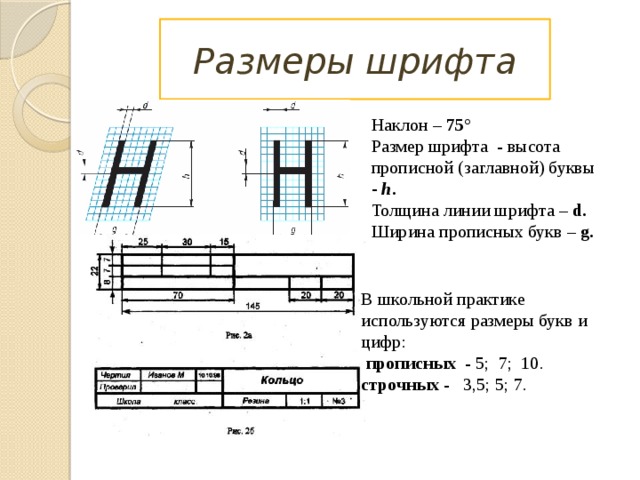
"Чертёжный шрифт"
Правила написания чертёжного шрифта. Высота и ширина букв и цифр.
Толщина линии обводки.
Расстояние между буквами, словами и основаниями строк.
«"Чертёжный шрифт"»
Чертежный шрифт
Чертежный шрифт ГОСТ 2.304-81 высота и ширина букв и цифр толщина линий обводки  расстояние между буквами, словами и основаниями строк
Чертежный шрифт ГОСТ 2.304-81
• высота и ширина букв и цифр
• толщина линий обводки
• расстояние между буквами, словами и основаниями строк
Размеры шрифта Наклон – 75° Размер шрифта - высота прописной (заглавной) буквы - h . Толщина линии шрифта – d. Ширина прописных букв – g.  В школьной практике используются размеры букв и цифр:  прописных - 5; 7; 10. строчных - 3,5; 5; 7.
Размеры шрифта
Наклон – 75°
Размер шрифта - высота прописной (заглавной) буквы - h .
Толщина линии шрифта – d.
Ширина прописных букв – g.
В школьной практике используются размеры букв и цифр:
прописных - 5; 7; 10.
строчных - 3,5; 5; 7.
Параметры № Ширина прописных (заглавных) 1 букв и цифр – g  Размер h Б, В, Д, И, Е, 4, 2 5 Ж, Ф, Ш, Щ 3 7 3 10 4 4  А, М, Ы, Х, Ю 4 6 6 4 5 Г, Е, З, С, 2,3,5,6,78,9 8 5 3  1 7 4 2 5 2 3 № Ширина строчных букв – g 1 Размер h 2 3 з, с а, б, в, г, д, е, и, к, л, н, о, п, р, у, х, ц, ч, ь, э, я 5 2 3 4 7 3 2,5  м, ы, ю, ъ 4 3,5 3 ж, т, ф, ш, щ 5 4 3,5 6 5 7 Параметры Размер шрифта Расстояние между буквами, цифрами и знаками - a 5 Расстояние между словами - e 7 1 Расстояние между основаниями строк - b 10 1,4 3 2 4,2 8,5 6 12 17
Параметры
Ширина прописных (заглавных)
1
букв и цифрg
Размер h
Б, В, Д, И, Е, 4,
2
5
Ж, Ф, Ш, Щ
3
7
3
10
4
А, М, Ы, Х, Ю
4
6
4
5
Г, Е, З, С, 2,3,5,6,78,9
8
5
3
1
7
4
2
5
2
3
Ширина строчных буквg
1
Размер h
2
3
з, с
а, б, в, г, д, е, и, к, л, н, о, п, р, у, х, ц, ч, ь, э, я
5
2
3
4
7
3
2,5
м, ы, ю, ъ
4
3,5
3
ж, т, ф, ш, щ
5
4
3,5
6
5
7
Параметры
Размер шрифта
Расстояние между буквами, цифрами и знаками - a
5
Расстояние между словами - e
7
1
Расстояние между основаниями строк - b
10
1,4
3
2
4,2
8,5
6
12
17
Правила написания чертежного шрифта:     1. Все надписи на чертеже должны быть выполнены от руки. 2. Начертание букв выполняйте по частям. Движение руки при выполнении прямолинейных элементов букв осуществляется сверху вниз или слева направо, а закругленных — движением вниз и влево или вниз и вправо. Стрелка указывает направление движения рук. 3. Одинаковые элементы различных букв, цифр, знаков следует выполнять одним и тем же приемом, что способствует выработке автоматизма при их написании. 4.Выдерживайте заданный наклон шрифта с помощью направляющих штрихов. 5. Строго соблюдайте конструкцию каждой буквы и соотношение высоты и ширины буквы 6. Старайтесь выдерживать такое расстояние между буквами, чтобы зрительно оно казалось одинаковым. 7. Четкость, ясность и удобство чтения чертежа зависят от качества его выполнения и правильного выбора размеров шрифта. 8. Все надписи на чертеже должны быть аккуратными.
Правила написания чертежного шрифта:
1. Все надписи на чертеже должны быть выполнены от руки.
2. Начертание букв выполняйте по частям. Движение руки при выполнении прямолинейных элементов букв осуществляется сверху вниз или слева направо, а закругленных — движением вниз и влево или вниз и вправо. Стрелка указывает направление движения рук.
3. Одинаковые элементы различных букв, цифр, знаков следует выполнять одним и тем же приемом, что способствует выработке автоматизма при их написании.
4.Выдерживайте заданный наклон шрифта с помощью направляющих штрихов.
5. Строго соблюдайте конструкцию каждой буквы и соотношение высоты и ширины буквы
6. Старайтесь выдерживать такое расстояние между буквами, чтобы зрительно оно казалось одинаковым.
7. Четкость, ясность и удобство чтения чертежа зависят от качества его выполнения и правильного выбора размеров шрифта.
8. Все надписи на чертеже должны быть аккуратными.
Подготовка к работе
Проверка полученных знаний Вопрос Ответ Чертежный лист заданных по ГОСТ ЕСКД размеров с рамкой и основной надписью Мягкость карандаша Замкнутый контур на чертежном листе, ограничивающий рабочее поле чертежа Высота шрифта Специальная таблица в правом нижнем углу рамки, содержащая основные сведения об изображении Формат А 4 М Основная надпись Размер шрифта Шрифт Графическая форма изображения букв, цифр и условных знаков, которые используются при выполнении чертежей  Рамка
Проверка полученных знаний
Вопрос
Ответ
Чертежный лист заданных по ГОСТ ЕСКД размеров с рамкой и основной надписью
Мягкость карандаша
Замкнутый контур на чертежном листе, ограничивающий рабочее поле чертежа
Высота шрифта
Специальная таблица в правом нижнем углу рамки, содержащая основные сведения об изображении
Формат А 4
М
Основная надпись
Размер шрифта
Шрифт
Графическая форма изображения букв, цифр и условных знаков, которые используются при выполнении чертежей
Рамка